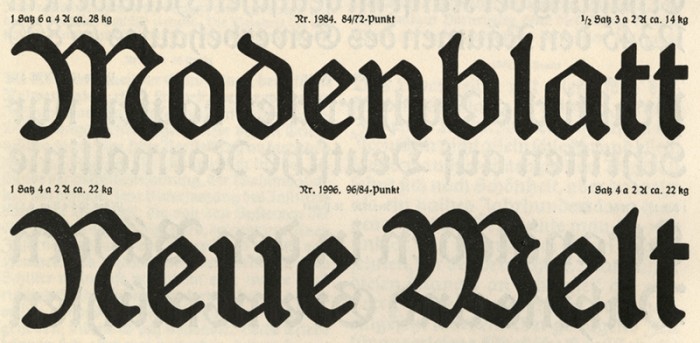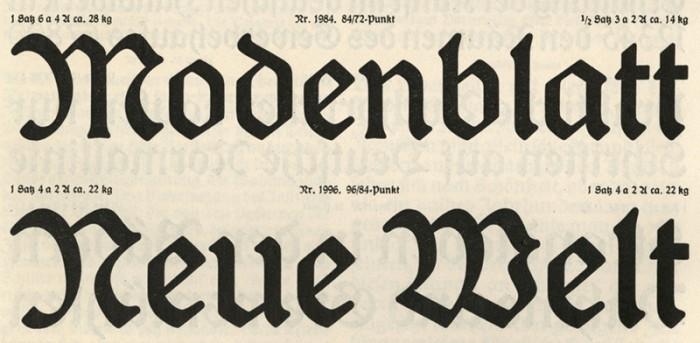
Gesucht: frakturverträgliche Antiqua, hohe Mittellänge, abgerundete Serifen
Suche Brotschrift mit folgenden Merkmalen:
abgerundete Serifen,
sehr hohe Mittellänge,
gemäßigter Kontrast,
ohne Schnick Schnack.
Sie sollte sich mit dieser sehr einfachen und verhältnismäßig weichen Fraktur »vertragen«.
Die Schriften werden nicht wirklich gemischt, aber ich möchte einen Text über die gezeigte Fraktur in Antiqua setzen, deshalb wünsche ich mir optische Gemeinsamkeiten. Mein erster Gedanke ging in Richtung Caslon, überzeugte mich aber nicht wirklich.
Ich schlage mal die Skolar von David Březina vor. Sie ist fantastisch ausgebaut, besitzt in den alternativen Glyphen auch ein einstöckiges a und hat einen eher kalligrafischen Duktus.
Die Rooney hatte ich lustiger Weise auch schon im Auge, ist ja auch 'ne Schöne, aber in der Kombination dann doch leider zu steif. Skolar, Ginkgo und Dederon: Auch schön, aber ich suche was mit stark gekehlten Serifen.
Die Argos und Lemon Serif sind Volltreffer. Die Argos gefällt mir einen Hauch besser, ist aber mit zwei Schnitten mehr als doppelt so teuer wie die Lemon Serif, die es grade im Angebot gibt :-D
Die Qual der Wahl.